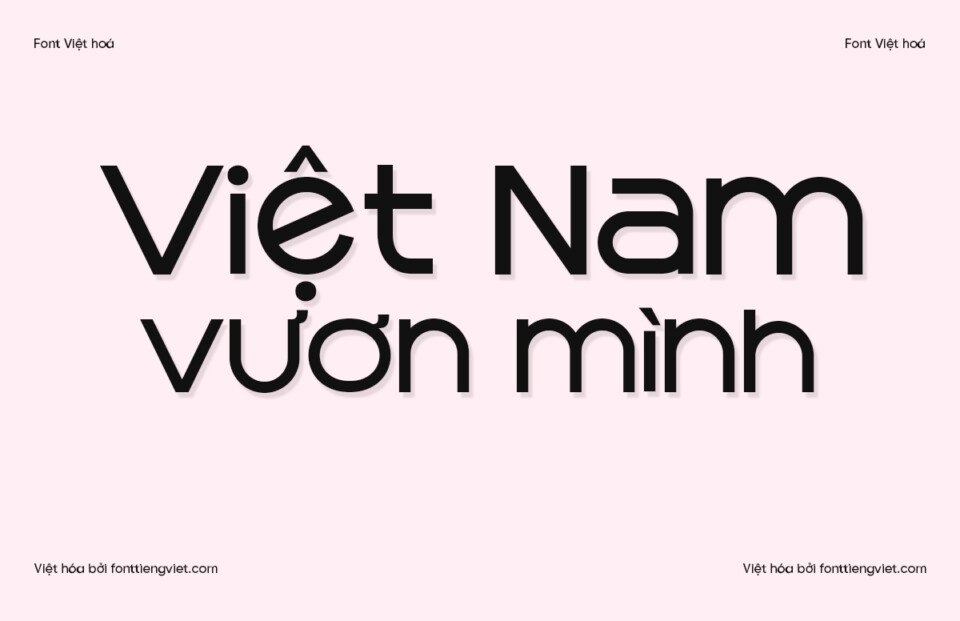
Font Việt hóa 1FTV VIP Gunken
Font Việt hóa 1FTV VIP Gunken – Lựa chọn hoàn hảo cho thiết kế hiện đại
Giới thiệu về Font Việt hóa 1FTV VIP Gunken
Trong thế giới đồ họa hiện nay, việc tìm kiếm một bộ font vừa mang tính thẩm mỹ cao vừa hỗ trợ đầy đủ tiếng Việt là điều vô cùng quan trọng đối với các nhà thiết kế chuyên nghiệp lẫn các bạn học sinh. Font Việt hóa 1FTV VIP Gunken nổi lên như một giải pháp hàng đầu, mang đến phong cách mạnh mẽ, hiện đại và vô cùng độc đáo. Khi nhắc đến khái niệm Font Miễn Phí, người dùng thường lo ngại về vấn đề lỗi dấu hoặc thiếu ký tự đặc trưng của ngôn ngữ chúng ta. Tuy nhiên, bộ font 1FTV VIP Gunken đã được đội ngũ kỹ thuật xử lý tỉ mỉ, giúp việc gõ văn bản trở nên mượt mà và chuẩn xác trên mọi phần mềm thiết kế từ đơn giản đến phức tạp.
Đặc điểm nổi bật của Font Việt hóa 1FTV VIP Gunken
Lý do khiến Font Việt hóa 1FTV VIP Gunken nhận được sự yêu thích nồng nhiệt nằm ở cấu trúc đường nét rất đặc trưng. Font sở hữu những nét chữ cứng cáp, dứt khoát nhưng không kém phần uyển chuyển, tạo cảm giác chuyên nghiệp cho mọi ấn phẩm. Đây là một kiểu font chữ display cực kỳ phù hợp để làm tiêu đề bài thuyết trình, thiết kế bìa sách giáo khoa hoặc trang trí báo tường cho nhà trường. Với sự kết hợp giữa tinh thần hiện đại và tính ứng dụng cao, bộ font này giúp các tác phẩm thiết kế trở nên nổi bật, thu hút ánh nhìn ngay từ giây phút đầu tiên. Hệ thống dấu câu được căn chỉnh thủ công, đảm bảo không bị chồng chéo hay rời rạc khi soạn thảo nội dung dài.
Ứng dụng thực tế của Font Việt hóa 1FTV VIP Gunken
Không chỉ giới hạn trong lĩnh vực nghệ thuật, Font Việt hóa 1FTV VIP Gunken còn được ứng dụng rộng rãi trong đời sống học đường và văn phòng. Đối với học sinh, các bạn có thể sử dụng font này để tạo ra những bài Powerpoint ấn tượng, giúp bài giảng của thầy cô thêm phần sinh động. Trong môi trường giáo dục, việc sử dụng font chữ rõ ràng, dễ đọc nhưng vẫn có cá tính riêng sẽ kích thích khả năng sáng tạo của người xem. Ngoài ra, các nhãn hàng cũng thường xuyên chọn 1FTV VIP Gunken để làm logo hoặc bao bì sản phẩm nhờ vào độ nhận diện cao và khả năng truyền tải thông điệp mạnh mẽ. Sự linh hoạt trong định dạng giúp font hiển thị tốt trên cả màn hình kỹ thuật số lẫn bản in giấy truyền thống.
Cách tối ưu hóa thiết kế với font chữ việt hóa
Để khai thác tối đa vẻ đẹp của Font Việt hóa 1FTV VIP Gunken, bạn nên kết hợp nó với các màu sắc tương phản hoặc đổ bóng nhẹ để tạo hiệu ứng 3D. Trong các bài thực hành đồ họa, việc điều chỉnh khoảng cách giữa các chữ cái (kerning) cũng giúp bố cục tổng thể trở nên hài hòa hơn. Lưu ý rằng vì đây là một font có cá tính mạnh, bạn nên sử dụng nó cho các tiêu đề lớn và kết hợp với những font không chân đơn giản cho phần nội dung chi tiết để tránh gây rối mắt cho người đọc. Sự cân bằng giữa phong cách nghệ thuật và tính khả dụng chính là chìa khóa tạo nên thành công cho bất kỳ bản thiết kế nào sử dụng bộ font VIP này.
Kết luận về bộ Font Việt hóa 1FTV VIP Gunken